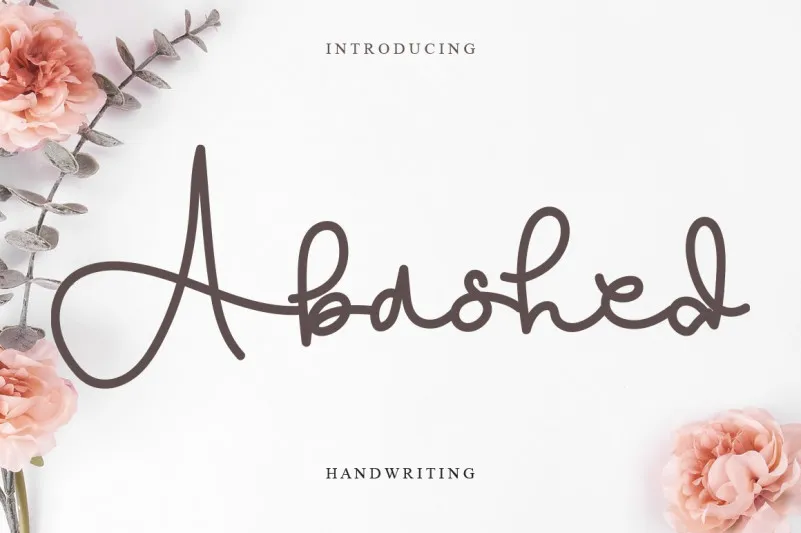
Abashed Font – Fonte Grátis
Abashed Font
A fonte Abashed é uma seleção elegante e fina, perfeitamente indicada para quem procura um touch delicado no seu trabalho de design. Sua letra escrita a mão suaviza projetos de forma sofisticada, tornando-a ideal para diversas aplicações, seja em cartazes, gráficos publicitários ou até mesmo em cards personalizados. Este elegante traço leva uma tonalidade mais romântica e leve aos seus trabalhos. Com um ar despojado e natural, a Abashed oferece um toque suave que torna qualquer projeto mais agradável e envolvente. É perfeita para adicionar um charme delicado à sua coleção de fontes, tornando-a uma opção versátil para os designers gráficos em busca de algo novo e único. Abashed é uma escolha perfeita para aqueles que buscam uma fonte escrita a mão para seus projetos de design. Ela não apenas adicionará um toque romântico, mas também oferecerá uma aparência fresca e atual, tornando-a um atalho eficaz à criatividade. Uma fonte despojada que vai muito bem em qualquer projeto, desde cartazes até designs de papelaria pessoal.